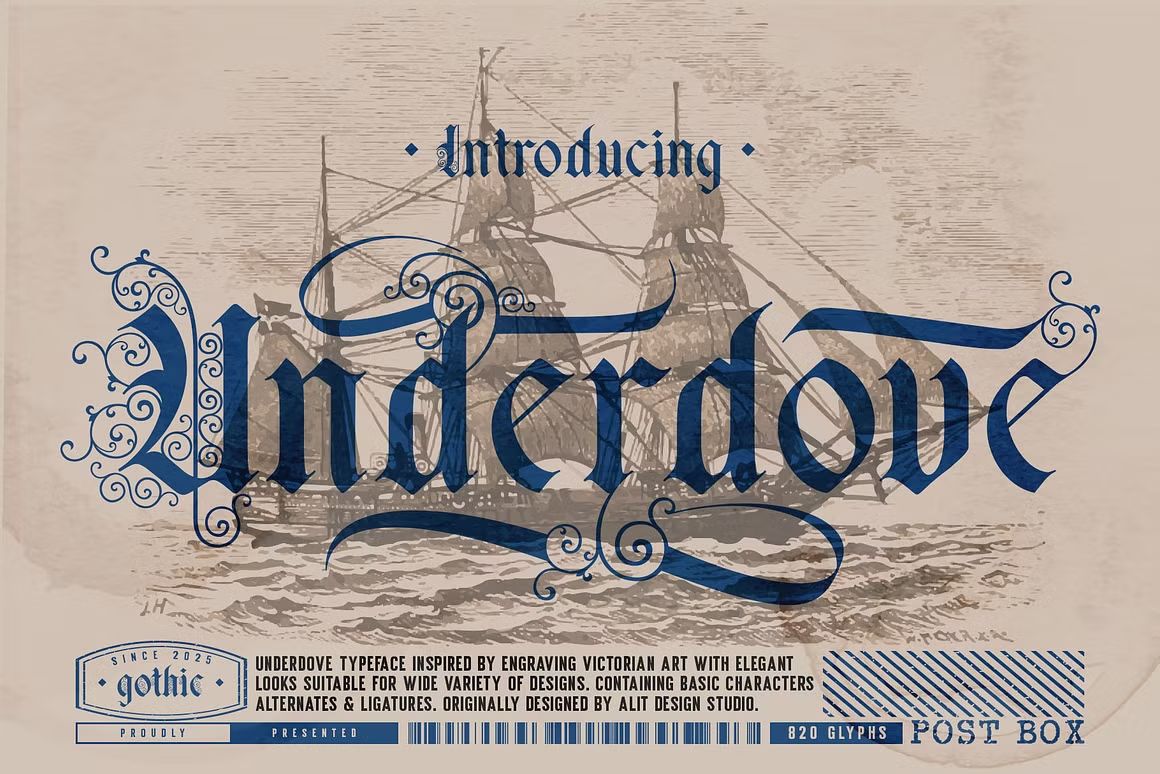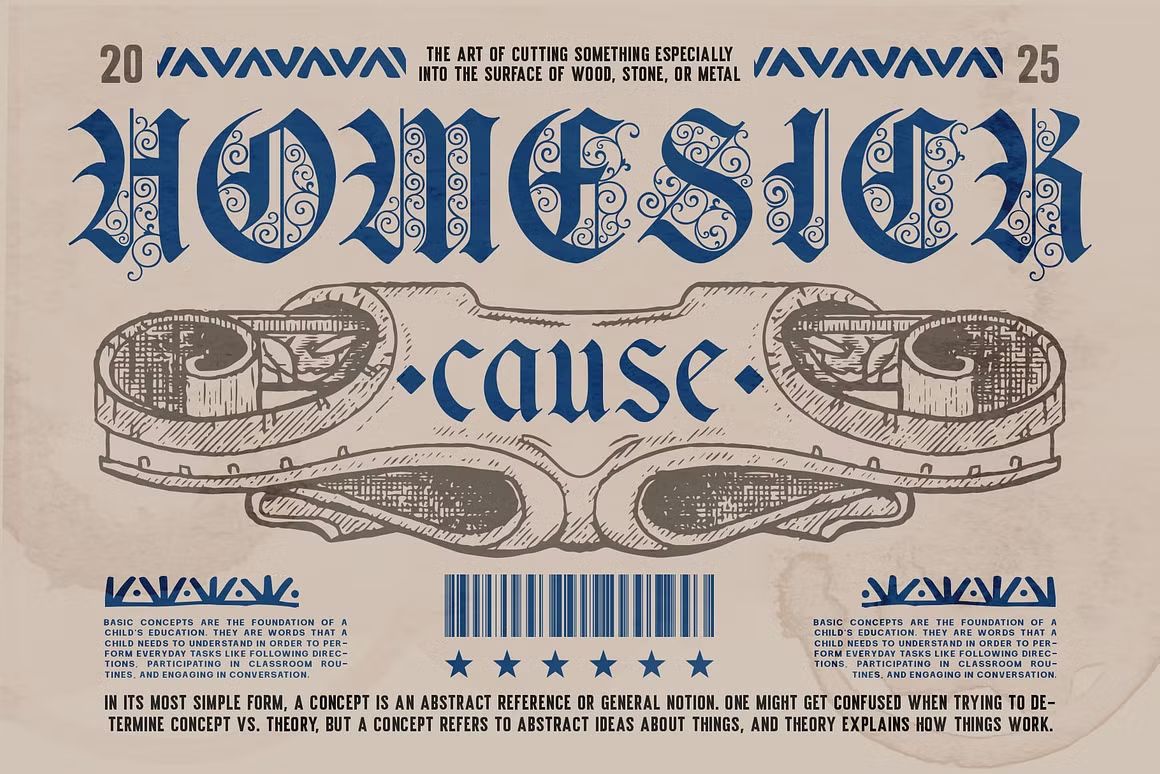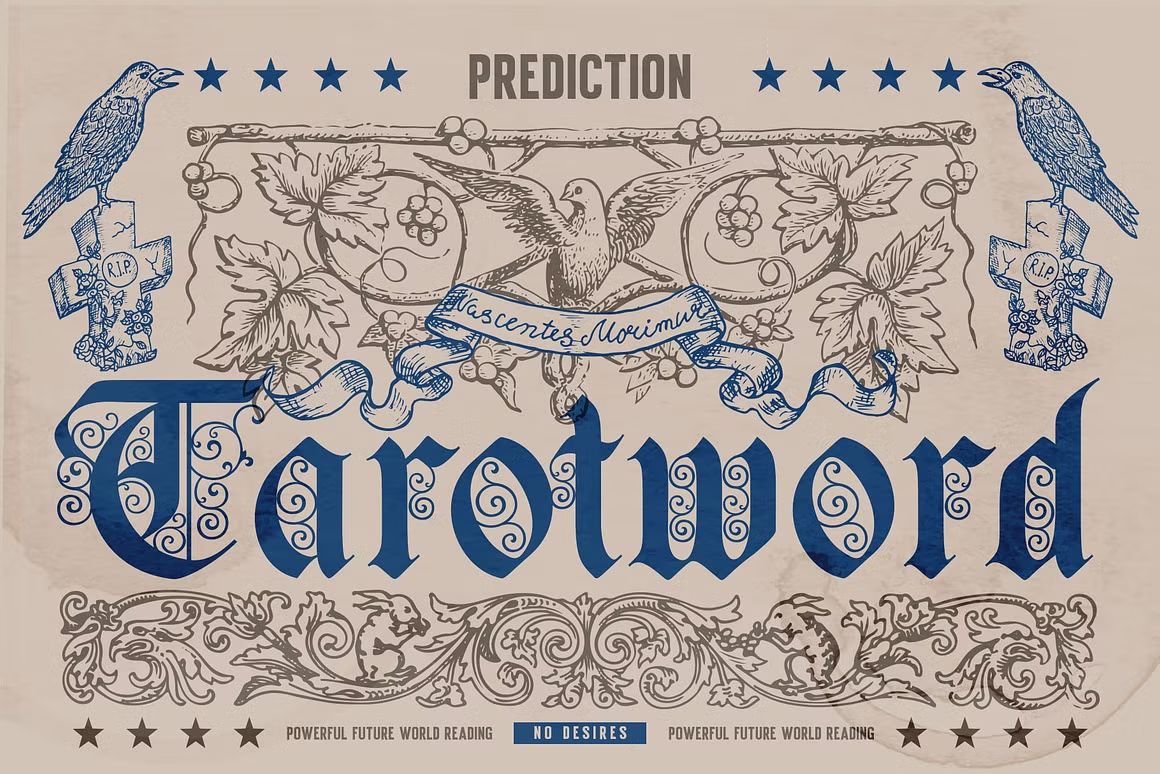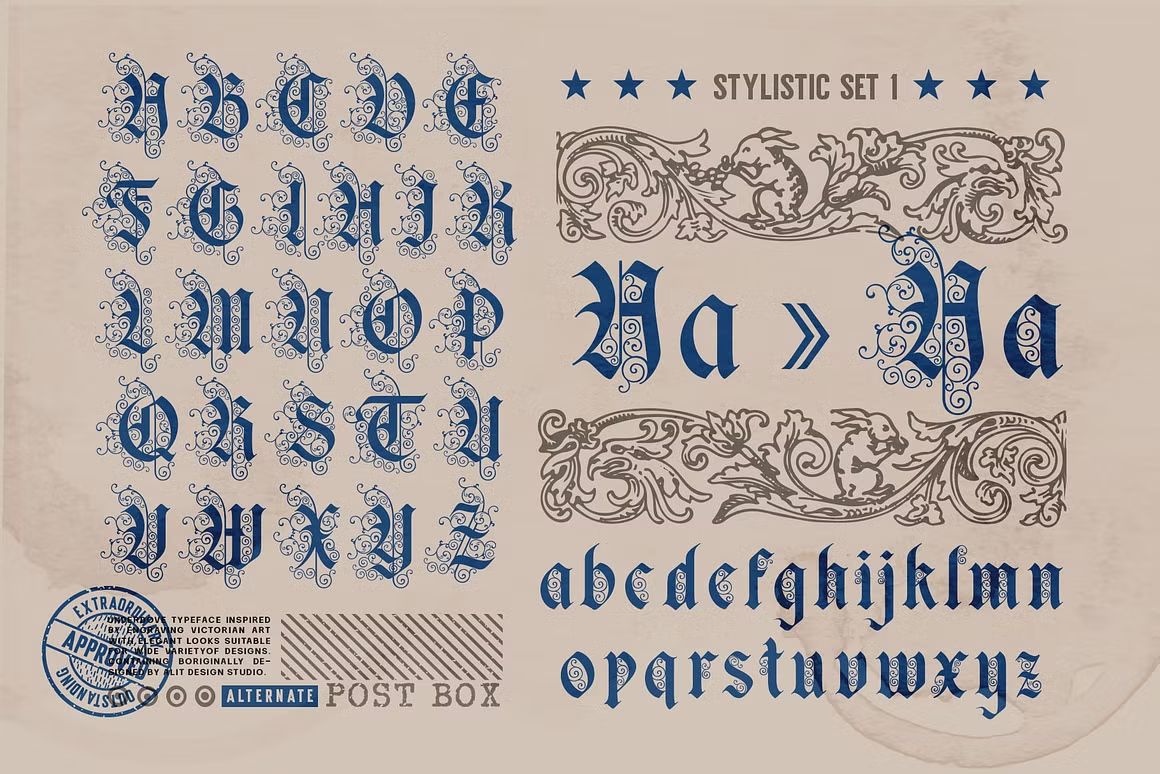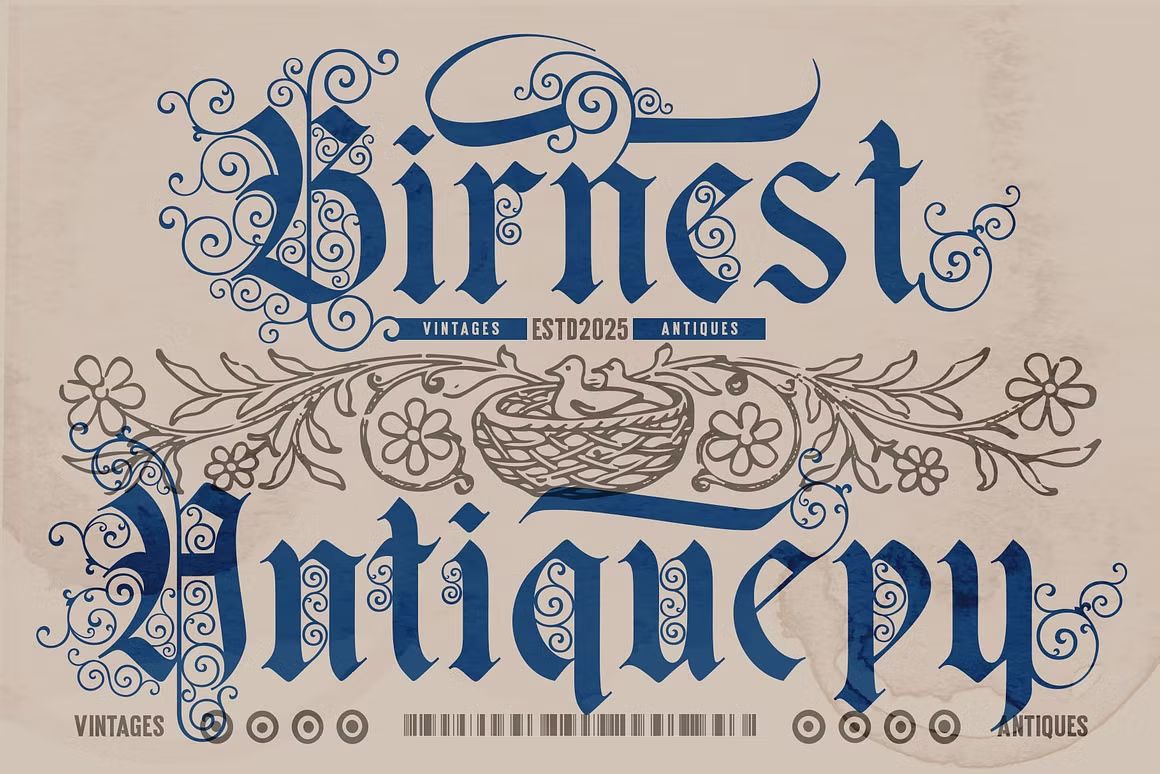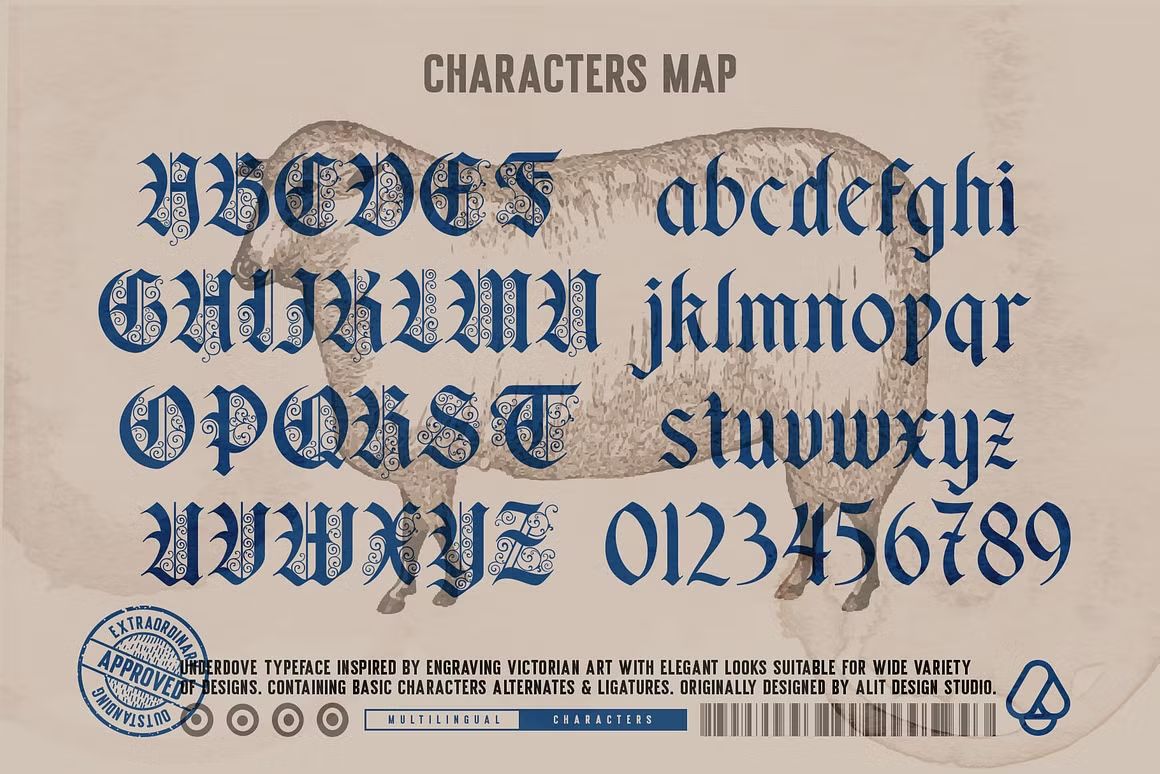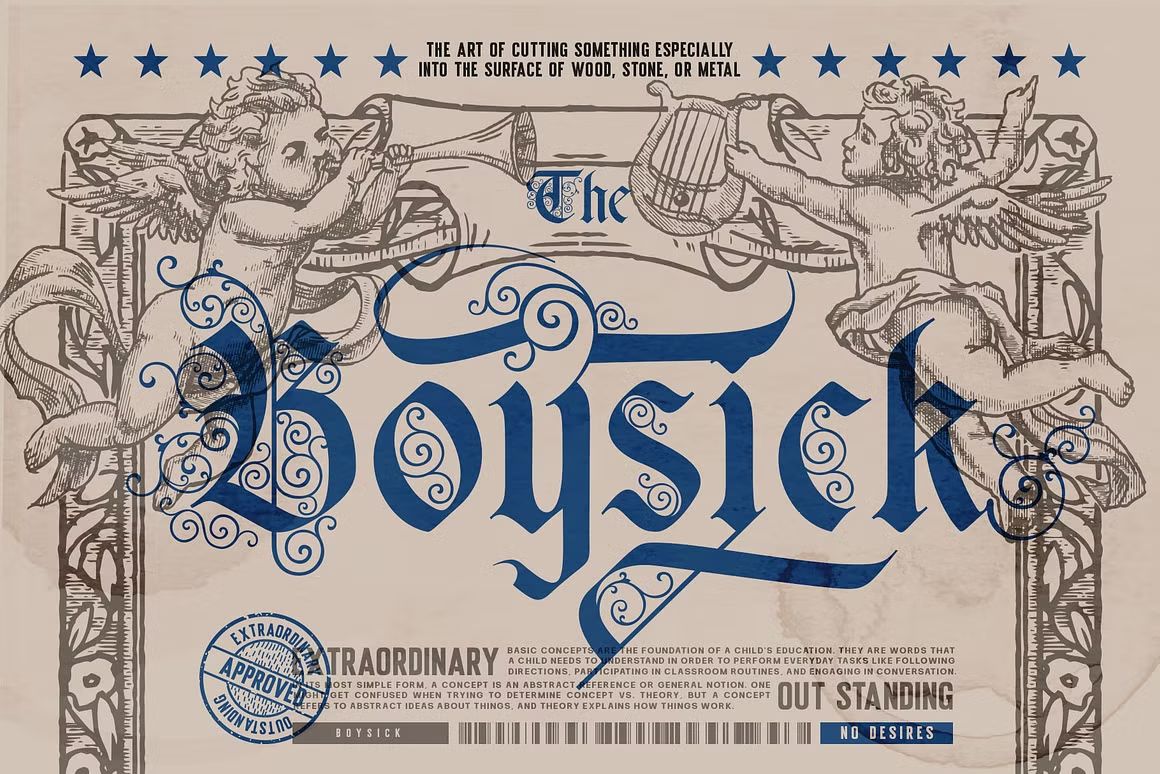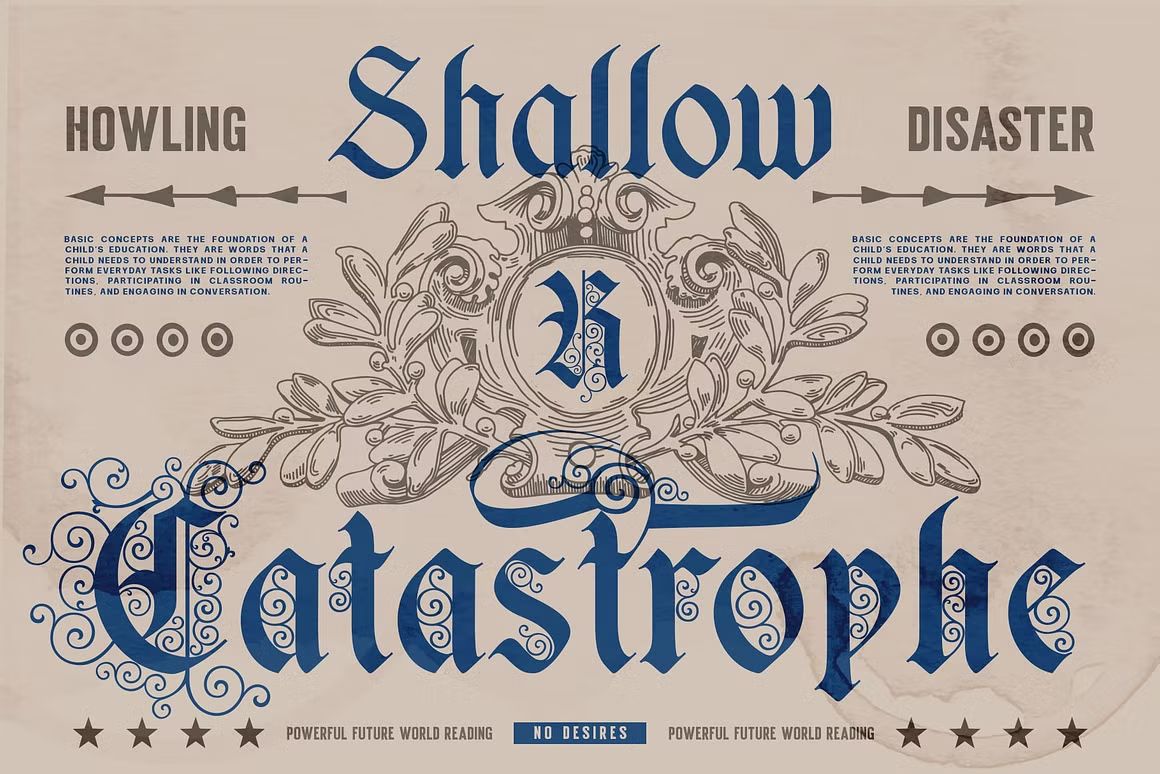
Underdove – Blackletter Font
Underdove adalah font blackletter bergaya gothic-modern yang kuat dan dramatis. Cocok untuk tattoo, musik, dan desain berani. Format OTF/TTF/WOFF, siap digunakan.
Underdove adalah font blackletter bergaya gothic klasik dengan sentuhan modern. Menampilkan bentuk huruf tegas, tajam, dan penuh ornamen khas, font ini sangat cocok untuk desain bertema vintage, tattoo, musik metal, poster, merchandise, dan branding berani. Dengan keseimbangan antara gaya tradisional dan estetika kontemporer, Underdove memberi kesan kuat dan dramatis dalam setiap karya.
• Gaya blackletter klasik dengan sentuhan modern
• Ideal untuk desain gothic, logo musik, dan poster dramatis
• Termasuk huruf besar, kecil, angka, dan simbol